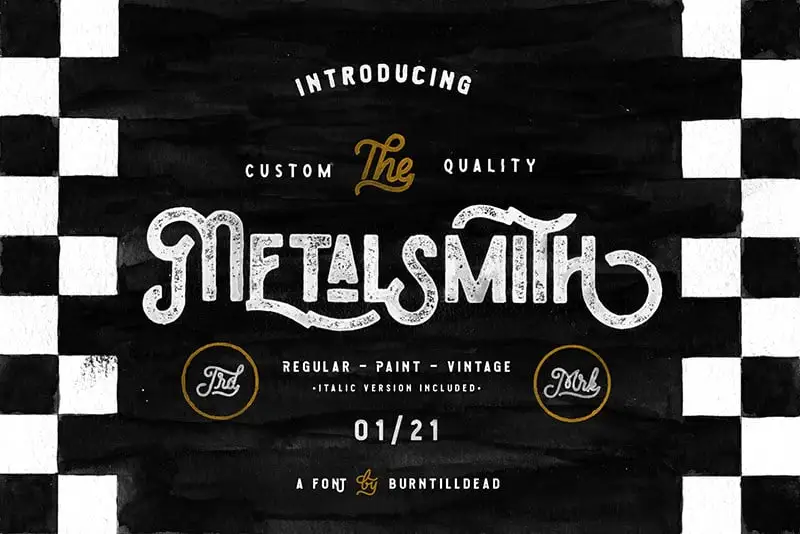
Através do “Metalsmith Display” font family, encontramos uma nova opção para aqueles que desejam adicionar um toque único e estiloso a qualquer projeto de design. Esta elegante tipografia customizada é perfeita para apresentar conteúdo de forma chamativa em materiais publicitários, revistas ou até mesmo em criações digitais. Criada pelo designer Burntilldead, esta fonte oferece um estilo distintivo capaz de diferenciar seu design do restante da concorrência. O “Metalsmith Display” é perfeito para usar em cenários onde você deseja destacar o texto, seja através de uma embalagem atrativa ou até mesmo em publicações online. Suas formas arredondadas e linhas finas proporcionam um visual atraente que se destaca, tornando-o adequado para diversos usos gráficos. O designer Burntilldead criou uma tipografia versátil que não apenas complementa o estilo do Metalúrgico, mas também adiciona um toque de personalidade aos designs em que ela é aplicada. A escolha da “Metalsmith Display” pode ser a solução perfeita para aqueles buscando manter sua identidade visual inovadora e estilosa.